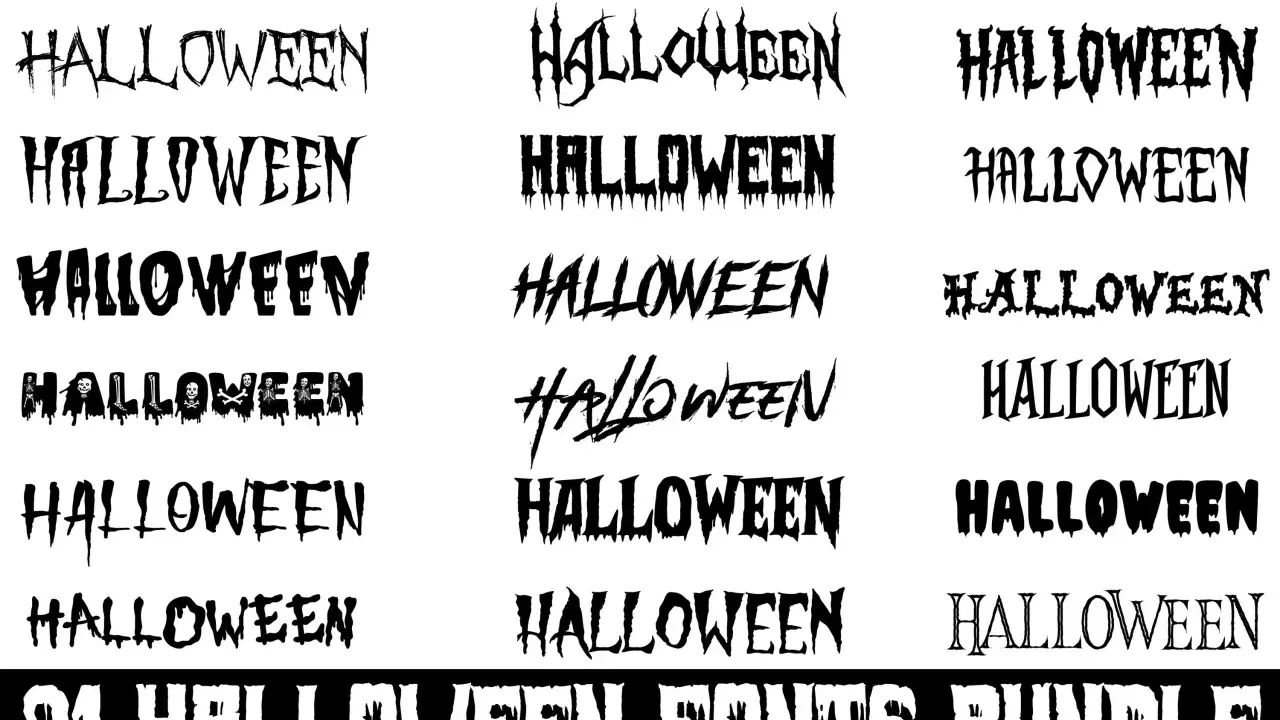
Mroczna typografia - Jak używać strasznych czcionek z głową?
Kolekcja 21 strasznych czcionek na Halloween, z kroplami i mrocznymi literami. Idealne na upiorne dekoracje.
Mroczny krój pisma działa najlepiej wtedy, gdy łączy klimat z czytelnością. Dobrze zaprojektowana straszna czcionka nie polega tylko na drapanych krawędziach czy kroplach „krwi” na literach, ale na konsekwentnym budowaniu nastroju: od kształtu znaków, przez odstępy, po kolor i tło. W tym tekście pokazuję, jakie style naprawdę robią wrażenie, gdzie ich używać i jak uniknąć efektu taniej dekoracji.
Najważniejsze rzeczy, które warto zapamiętać
• Horrorowy font ma przede wszystkim wywoływać emocje, ale nadal dawać się przeczytać w 1–2 sekundy.
• Najmocniej działają style blackletter, distressed, dripping, stencil i mocne fonty displayowe.
• Na jeden projekt zwykle wystarcza jeden dekoracyjny krój i jeden prosty font pomocniczy.
• Do tekstu głównego lepiej nie używać ozdobnych krojów; zostaw je na tytuł, hasło lub krótką zajawkę.
• Na ekranie pilnuj kontrastu co najmniej 4.5:1 dla zwykłego tekstu i wielkości 14–16 px w materiałach cyfrowych.
• Najlepszy efekt daje nie sam font, tylko połączenie kroju, koloru, światła i odpowiedniego marginesu oddechu.
Co sprawia, że krój wygląda groźnie
Nie każdy krój z „mrocznym” stemplem wygląda naprawdę niepokojąco. W praktyce o efekcie decydują konkretne cechy: asymetria, ostre zakończenia, pęknięcia w kreskach, zniszczona faktura i ciasne odstępy między literami. Taki zestaw sprawia, że napis wydaje się bardziej napięty, niestabilny albo wręcz agresywny.
Ja zwykle patrzę na to w bardzo prosty sposób: im bardziej litera przypomina coś uszkodzonego, wygiętego, ostrego lub organicznie „zepsutego”, tym mocniej kojarzy się z horrorem. W typografii ważny jest też kerning, czyli ręczne ustawienie odstępów między konkretnymi parami liter. Jeśli zrobisz go zbyt ciasno, tekst zacznie się dusić; jeśli zbyt luźno, straci napięcie i zrobi się przypadkowy.
• Asymetria daje wrażenie chaosu i braku kontroli.
• Złamane kreski sugerują rozpad, uszkodzenie albo brutalność.
• Wysoki kontrast między grubymi i cienkimi elementami przyciąga uwagę, ale łatwo go przesadzić.
• Zwężone proporcje budują duszny, klaustrofobiczny charakter.
• Tekstura potrafi dodać brudu, starości lub krwistego efektu, jeśli nie zdominuje kształtu liter.
Gdy już wiem, co robi z literami efekt grozy, łatwiej dobrać konkretny styl i uniknąć przypadkowości.
Najmocniejsze style w mrocznej typografii
W horrorowej typografii nie ma jednego uniwersalnego rozwiązania. Inaczej pracuje krój gotycki, inaczej zniszczony display, a jeszcze inaczej font z kroplącym efektem. Wybór zależy od tego, czy chcesz uzyskać klimat klasycznego horroru, komiksowej grozy, czy bardziej surowego thrillera.
Styl Efekt Najlepsze zastosowanie Na co uważać
Blackletter / gotyk Historyczny, ceremonialny, ciężki Okładki, festiwale, metal, klasyczny horror Łatwo przesadzić z ornamentem i stracić czytelność
Distressed / grunge Zniszczony, brudny, niepokojący Plakaty, teasery, social media, gry Tekstura nie może zjadać liter
Dripping / slime Dosłowna groza, komiksowość, czasem humor Halloween, eventy, krótkie hasła Działa najlepiej na 2–5 słów
Stencil / wojskowy Napięcie, surowość, kontrola Thrillery, survival, gry, plakaty akcji Potrzebuje mocnego tła i dobrego kontrastu
Display z ostrymi zakończeniami Elegancki niepokój, bardziej filmowy niż dosłowny Tytuły filmowe, branding sezonowy Wymaga dopracowanego kerningu
Jeśli potrzebujesz punktu startowego, do lżejszego, komiksowego efektu dobrze sprawdza się Creepster, a do bardziej agresywnego nastroju Nosifer lub gotyckie kroje w stylu UnifrakturCook. W takich przypadkach font sam w sobie robi połowę pracy, ale dopiero układ i tło decydują, czy efekt będzie dobry, czy tylko głośny.
Sam styl to dopiero punkt wyjścia; ważniejsze jest to, gdzie i jak go użyjesz.
Gdzie taki font działa najlepiej, a gdzie szkodzi
Ozdobne, straszne kroje najlepiej pracują tam, gdzie komunikat jest krótki i ma natychmiast złapać uwagę. Dlatego widzę je przede wszystkim w tytułach plakatów, teaserach, okładkach, grafikach eventowych i w brandingach sezonowych, na przykład przy Halloween albo premierach gier i filmów. W takich miejscach font ma być nośnikiem emocji, a nie zwykłym narzędziem do czytania długiego tekstu.
• Plakat lub baner - 2–6 słów wystarczy, jeśli reszta kompozycji jest dobrze ustawiona.
• Okładka książki lub albumu - mocny krój buduje obietnicę gatunku.
• Social media - działa w miniaturze, więc trzeba pilnować grubości liter i kontrastu.
• Hero section na stronie - dobry na krótki slogan, zły na dłuższy akapit.
• Opakowanie i etykieta - szczególnie przy limitowanych edycjach, produktach sezonowych i kampaniach promocyjnych.